Der 9. Teil der Reihe Typografie in Frankfurt besteht aus 10 Fotos, hauptsächlich mit Gestaltungen aus dem Bereich Gastronomie. Meine Favoriten sind die Suppenküche »Souper“ und das »Café Libretto«. Schriftauswahl passend zum Thema, dazu ein ebenso passendes Objekt, das nicht einfach nur neben oder über dem Namen platziert, sondern sehr schön eingebunden wurde. So wird’s gemacht.
SOUPER
CAFÈ LIBRETTO
Waren wir nicht alle einmal der kleine Junge mit den großen, auf die drei Bällchen Eis in der Waffel gerichteten Augen? Gelungene Illustration, das Drumherum vielleicht ein bisschen zu mächtig?
LOLLI EIS
Sonne und Wasser sowohl farblich im Text wie auch im Logo aufgegriffen, lediglich die Abstände zwischen den Buchstaben sind manchmal zu gering oder zu groß geraten, finde ich.
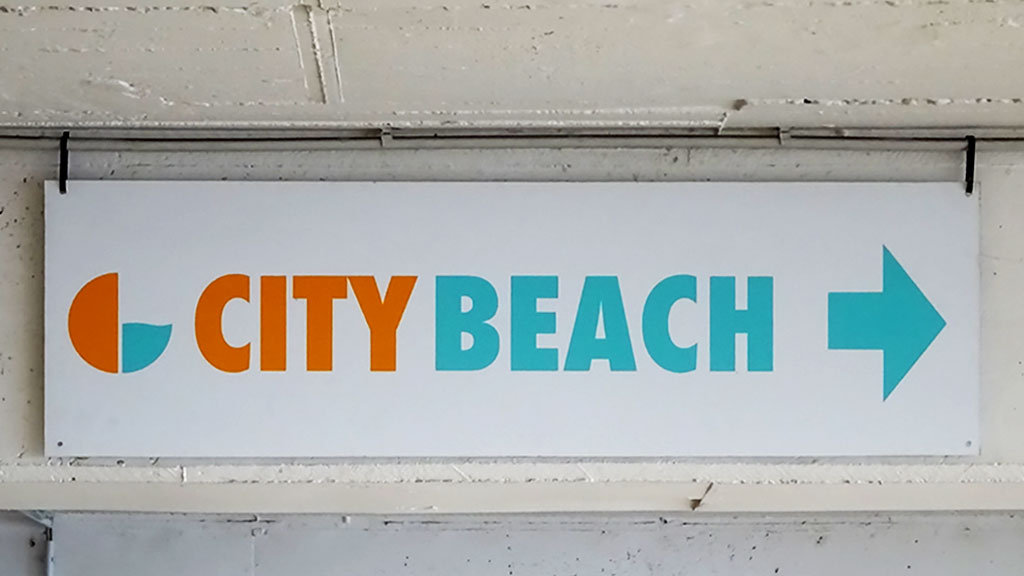
CITY BEACH
Zu sehen sind die obere Hälfe eines Footballs und die untere eines Burgers. Die freistehende Naht des Footballs finde ich nicht optimal gelöst. Da hätte entweder noch ein Patty in derselben dunklen Farbe dahinter oder wenigstens auch die Naht eingefärbt gehört.
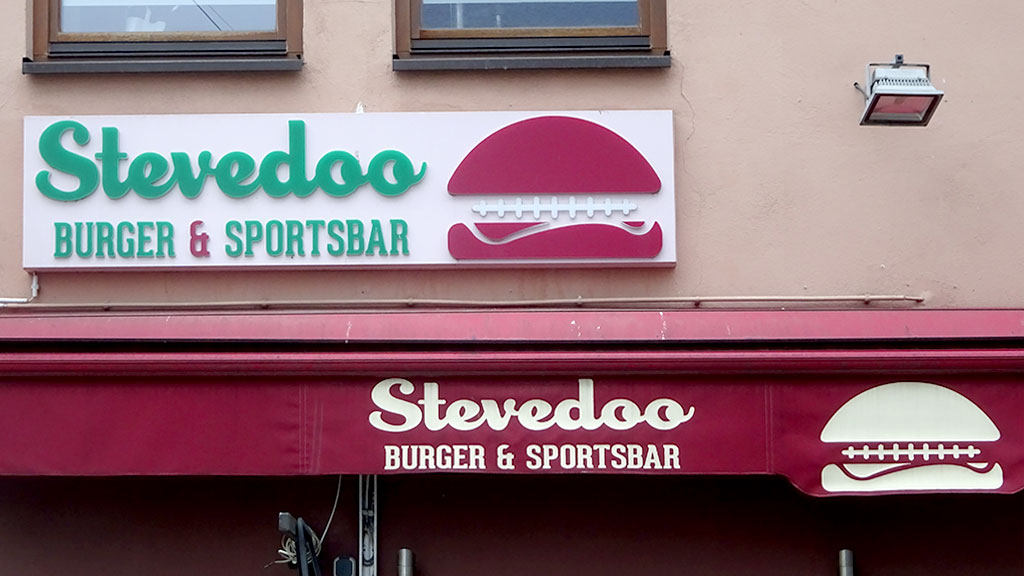
STEVEDOO
Das ehemalige Lala Mamoona wurde schon vor längerer Zeit zur »Hausbar« umfunktioniert. Die komplett linksbündig ausgerichtete Gestaltung des Schildes greift das kleine Häuschen, das die Location nunmal ist, auf und präsentiert sich insgesamt dezent und elegant.
HAUSBAR
Schwarze Schrift auf einfarbigem Hintergrund, dazu nur Minuskeln verwendet und das alles in ein Quadrat gepackt. Für mich passt sowas wunderbar. Nicht verstanden habe ich allerdings, wofür diese zwei Elemente an den Wörtern stehen, bei denen zudem der Übergang von der Geraden zu Rundung etwas unrund wirkt.
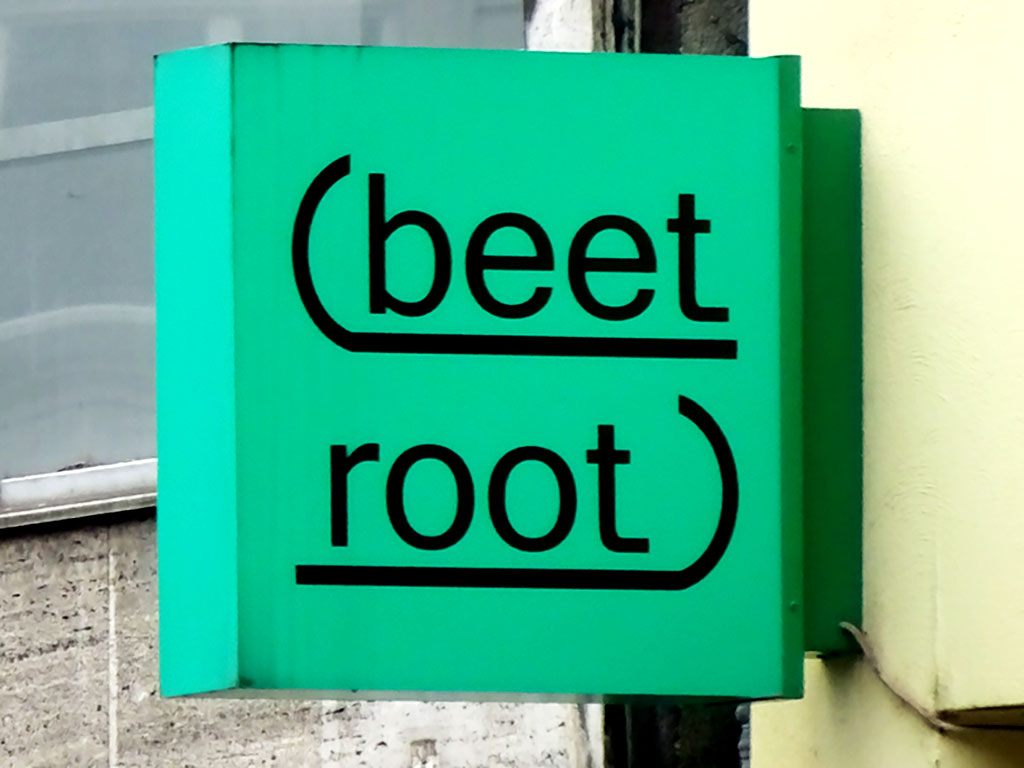
BEET ROOT
Angeschnittene Buchstaben, Buchstaben die über eine Zeile verlaufen, Buchstaben, deren Höhe über zwei Zeilen verläuft, farbige Buchstaben – mir ist das in Summe zu viel. Vielleicht auch der Grund, warum der Name in anderer, klarer Weise direkt darunter nochmal auftaucht?
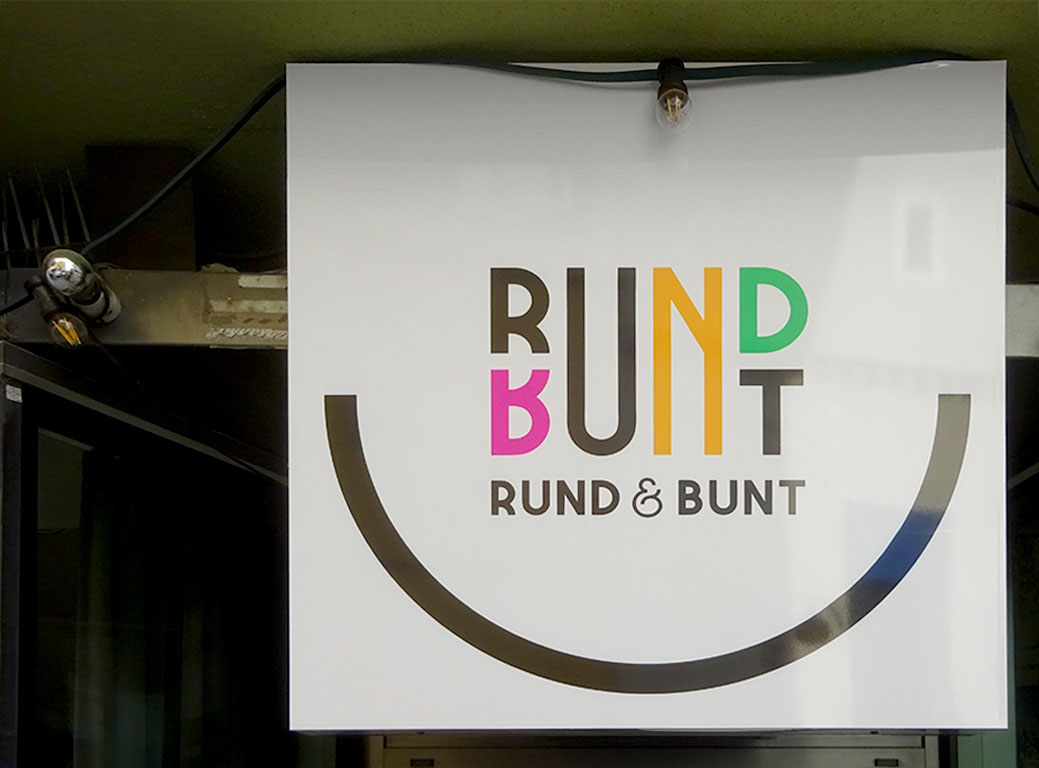
RUND & BUNT
So einfach kann’s sein: Zwei Wörter, eines in Schreibschrift, das andere ausschließlich aus serifenlosen Großbuchstaben, dazu weiß und schwarz, zack, fertig.
PM CLUB
Wenn eine Location den Tiger in dir wecken kann, dann die BB Bar. Wunderbar.
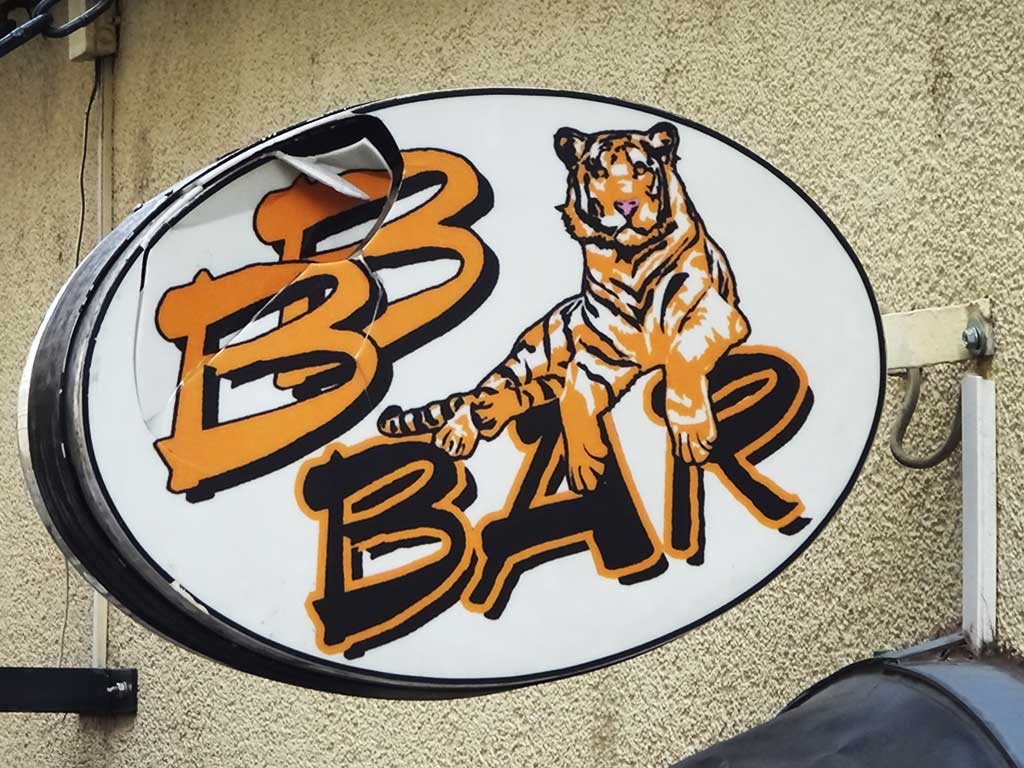
BB BAR